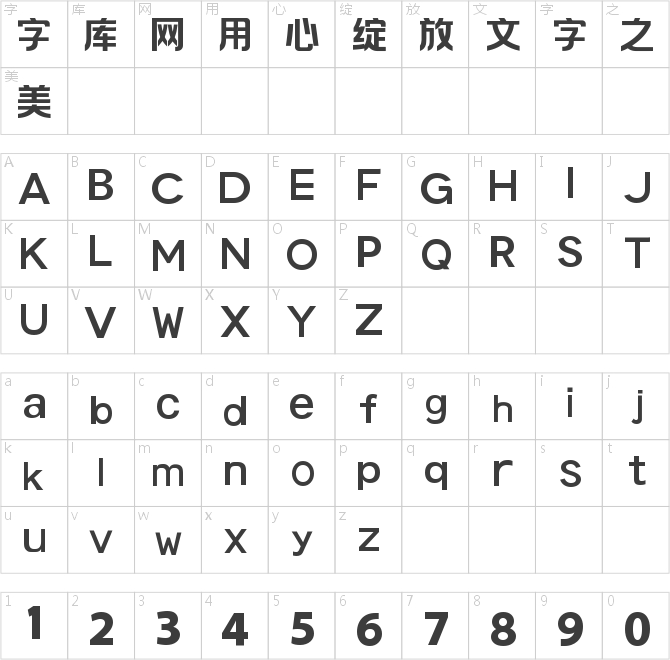
字體名稱: 淘寶買菜體
﹤p﹥﹤p﹥淘寶買菜攜手通義錦書,傾力打造了一款獨具匠心的AI個性化字體。這款智能AI字體不僅擁有豐富的中文字符庫,覆蓋GB2312標準,包含超過6974個漢字,更通過智能AI技術,賦予字體獨特的質感和生命力。我們精心挑選了7套質感圖片,現已廣泛應用于淘寶買菜的各個場景,顯著提升了運營和設計團隊的工作效率,達到了20%的效率提升。﹤/p﹥﹤p﹥&﹔nbsp﹔現這款字體向所有個人和組織開放,永久免費商用。這不僅是對創新精神的致敬,也是我們對普惠理念的堅持。淘寶買菜與通義實驗室將持續攜手,不斷探索AI技術的無限可能,致力于將更智能、更高效的解決方案帶給每一位用戶。讓我們一起迎接一個更加智能、更加個性化的未來。﹤/p﹥﹤/p﹥